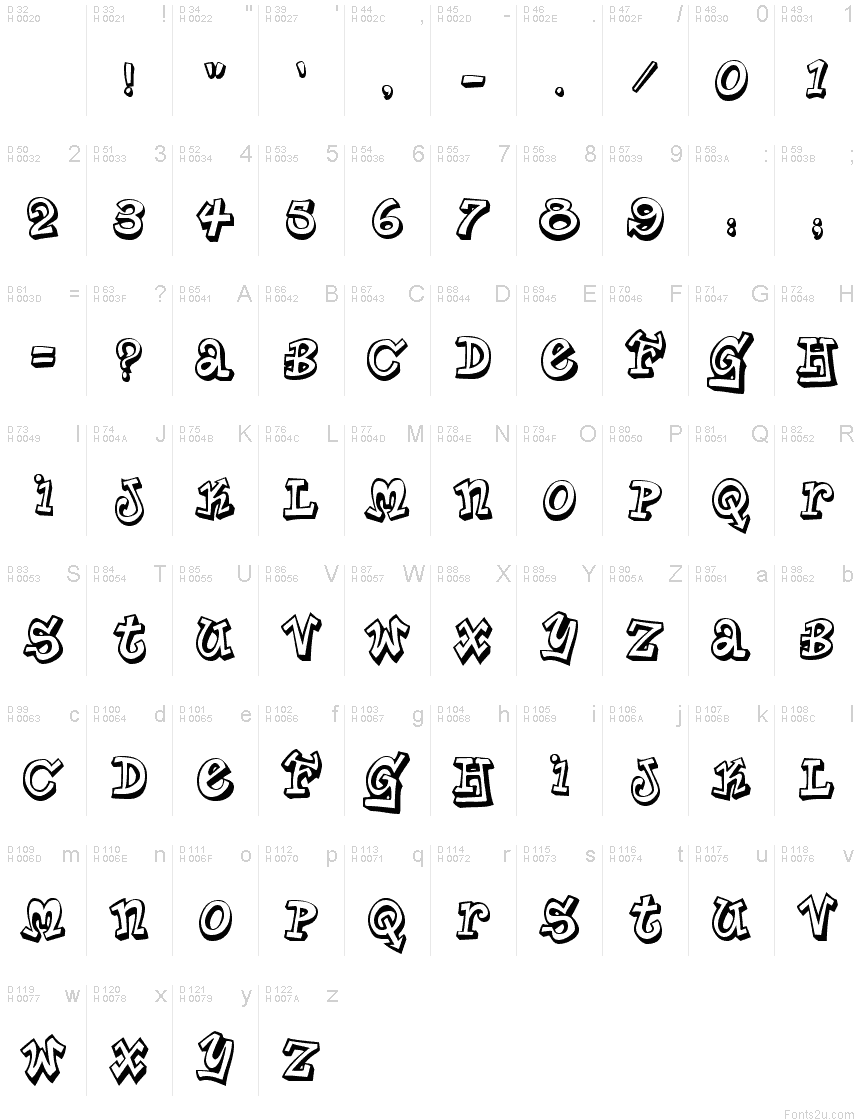
Planet Benson autorstwa Raya Larabie to darmowy, trójwymiarowy font typu display ze skocznym, ręcznie rysowanym charakterem, który wygląda jak wyjęty prosto z 1997 roku. Litery opierają się na masywnych, komiksowych kształtach i grubych, przesuniętych cieniach, a luźne, nierówne kontury sprawiają, że cały font jest zabawny, a nie przesadnie wygładzony.
Sprawdza się świetnie na okładkach komiksów, plakatach dla dzieci, planszach tytułowych w stylu arcade, naklejkach i krótkich projektach logo, gdzie darmowy font ma natychmiast nadać komiksowej energii. Ponieważ cień jest wbudowany bezpośrednio w litery, Planet Benson naturalnie pasuje do dużych nagłówków, efektownych opakowań i krótkich napisów, które mają przyciągać wzrok i być wyraziste.
Planet Benson